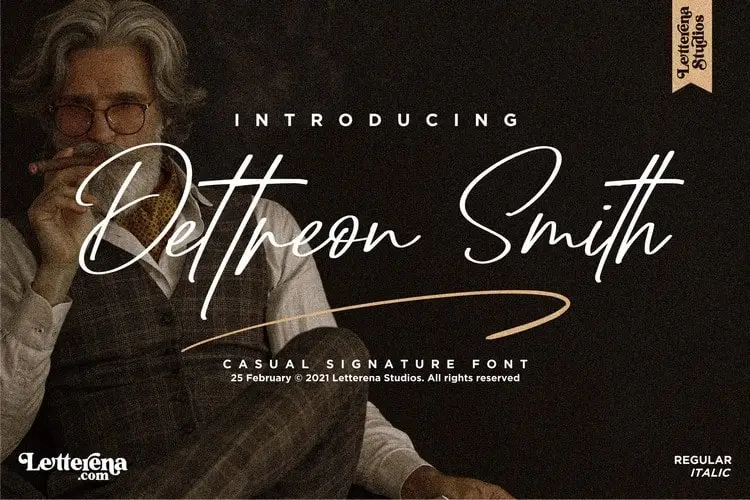
Dettreon Smith Script Font – Download Grátis
A fonte Dettreon Smith Script é uma escolha perfeita para aqueles que desejam trazer elegância e sofisticação aos seus projetos digitais e impressos. Se você está buscando um gatilho para seus trabalhos de logomarca, identidade visual ou design gráfico em geral, esta fonte é definitivamente uma opção ideal. Com seu charme único e sua tipografia script elegante, ela se adequa perfeitamente a vários tipos de projetos, incluindo logos, marcas, designs para home office, embalagens de produtos, mugs personalizados, cartões de visitas, convites de casamento ou festa, selos, fotos e até mesmo marca d’água. A Dettreon Smith Script é a fonte ideal para suas entregas que exigem um toque de sofisticação. Descubra o brilho da elegância com essa fonte única e originalmente criada por Letterena Studios.